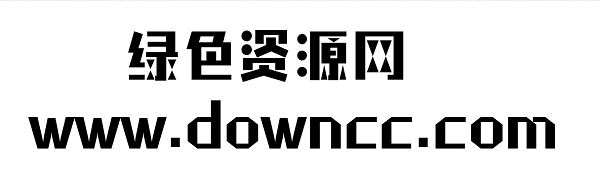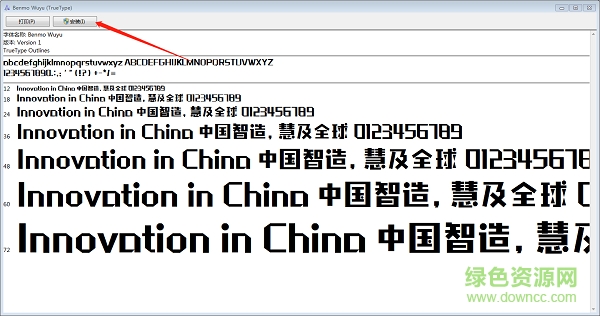
本墨物語(yǔ)字體是一款風(fēng)格上非常規(guī)章整潔的字體,能夠給用戶一種非常正式化的感覺,字體整體看起來較粗,適用于割裂標(biāo)題以及比較醒目的多個(gè)地反,喜歡的用戶快來綠色資源網(wǎng)下載吧!
本墨物語(yǔ)字體是一款由本墨字庫(kù)提供的中文簡(jiǎn)體藝術(shù)字體,擁有簡(jiǎn)潔整齊的字體外觀和橫細(xì)豎粗的字體筆畫,造型獨(dú)特并且美觀,支持中文簡(jiǎn)體、拼音字母、數(shù)字符號(hào)等輸出格式,適合應(yīng)用在廣告設(shè)計(jì)、平面制作、印刷品、影視字幕等多種領(lǐng)域使用!
-其線條粗壯有力,整體效果非常出色,給人很強(qiáng)的視覺沖擊力,
-能夠應(yīng)用于文本裝潢、信息展示、網(wǎng)頁(yè)設(shè)計(jì)、 篆刻制模、數(shù)據(jù)制作、裝潢設(shè)計(jì)、計(jì)算藝術(shù)設(shè)計(jì)、視覺設(shè)計(jì)、字帖等一切合法應(yīng)用場(chǎng)景!